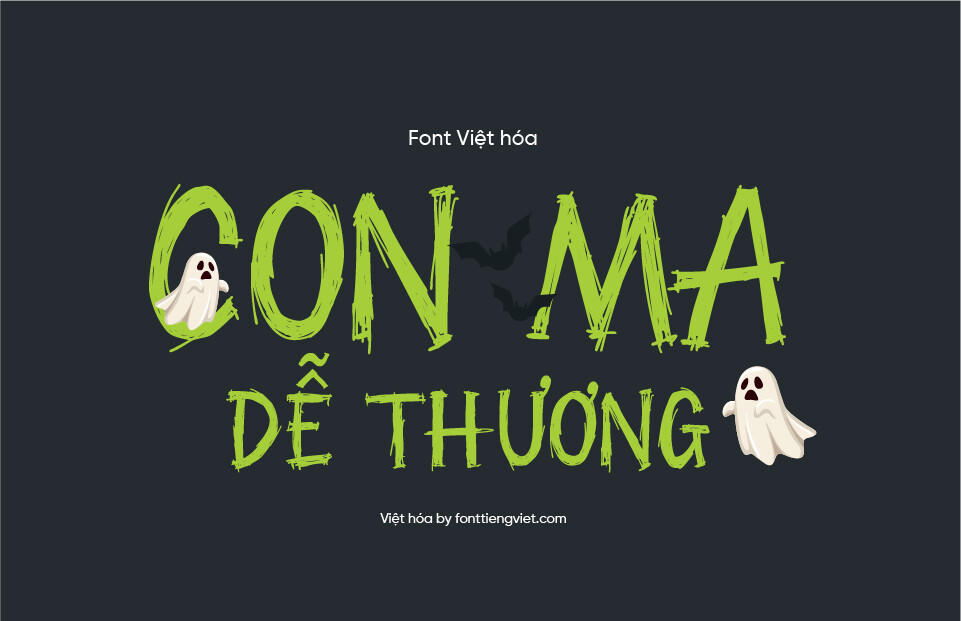
Font Việt hóa 1FTV VIP Rhope – Halloween
Chào mừng các bạn đến với thế giới sáng tạo đầy màu sắc dành cho học sinh và giáo viên. Nếu bạn đang tìm kiếm một bộ Font Miễn Phí để chuẩn bị cho các dự án trường học hay trang trí bảng tin lớp học vào dịp lễ hội, thì Font Việt hóa 1FTV VIP Rhope – Halloween chính là lựa chọn hoàn hảo nhất. Đây là một bộ font chữ mang phong cách kinh dị nhưng vẫn giữ được nét tinh tế, hiện đại, giúp các sản phẩm thiết kế của bạn trở nên chuyên nghiệp và bắt mắt hơn bao giờ hết.
Đặc điểm nổi bật của Font Việt hóa 1FTV VIP Rhope – Halloween
Thiết kế sáng tạo và đậm chất lễ hội
Bộ Font Việt hóa 1FTV VIP Rhope – Halloween sở hữu những đường nét uốn lượn sắc sảo, gợi liên tưởng đến những cành cây khô hay những vệt sơn loang lổ đặc trưng của mùa Halloween. Điểm cộng lớn nhất là bộ font này đã được tối ưu hóa tiếng Việt hoàn chỉnh, giúp các bạn học sinh dễ dàng soạn thảo các nội dung thuyết trình hoặc làm thiệp mời mà không lo bị lỗi hiển thị các dấu câu đặc thù.
Tính ứng dụng cao trong môi trường học đường
Không chỉ dùng cho mục đích cá nhân, bộ chữ này còn rất phù hợp để thiết kế tiêu đề bài giảng điện tử, làm bìa báo tường hoặc tạo các trò chơi tìm hiểu văn hóa phương Tây. Sự kết hợp giữa yếu tố ma mị và tính thẩm mỹ cao giúp người xem dễ dàng bị thu hút vào nội dung bạn muốn truyền tải.